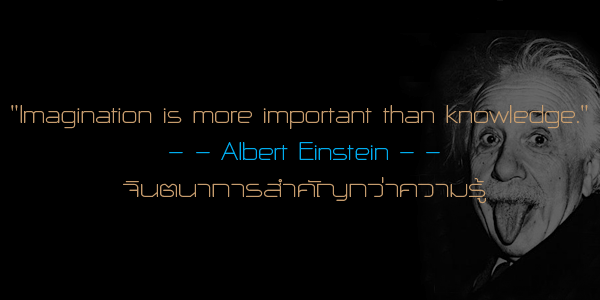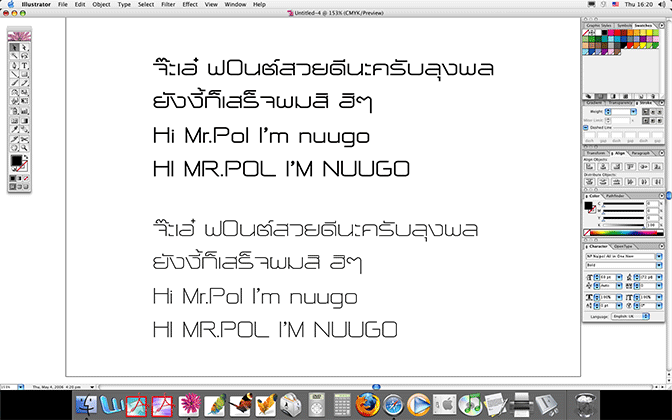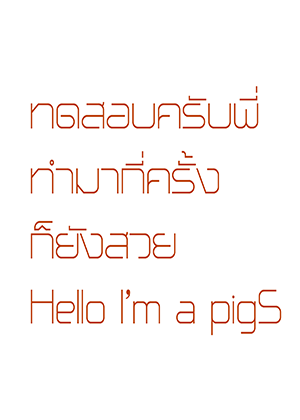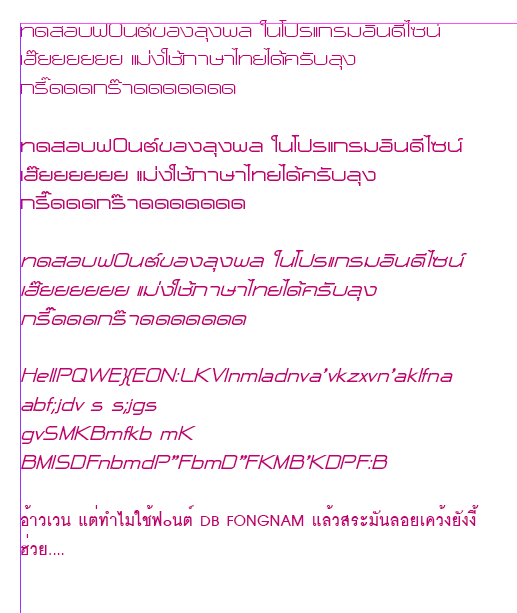
ฟอนท์เก่าเอามาทำใหม่ ช่วยวิจารณ์+ทดสอบกันหน่อยครับ  กรี๊ดดดดด
มีการปรับเปลี่ยนใหม่ทั้งหมด โดยเฉพาะพวก จ ฉ น ม ท พวกนี้ครับตัวเดิมมันหยักน้อยเวลาใช้ตัวเล็กมันไม่แจ่ม
ตัวหนา ตัวเอน ทำใหม่หมด
จัด kerning เพิ่มเติม
ทำเป็นฟอนท์ .otf ซึ่งเป็นแพลตฟอร์มใหม่ล่าสุดของฟอนท์ จึงอยากให้เอาไปลองกันหน่อยครับ เพราะเข้าใจว่าในอนาคตอาจจะมีการทำฟอนท์ .otf กันเป็นส่วนใหญ่ รวมทั้งผมต้องการทดสอบตัวเทมเพลตด้วยครับ เท่าที่เจอตัวเทมเพลตถ้าทำเป็น .otf จะมีปัญหาบางตัวกับ Photoshop CS ซึ่งต้องเปลี่ยนชื่อบาง Glyph เพราะฉะนั้นใครอย่าเพิ่งเอาไปทำเป็นฟอนท์ .otf นะครับ รอเวอร์ชันต่อไป โดยเฉพาะใครใช้แมครบกวนแจ้งผลด้วยนะครับ
รวมทั้งช่วยวิจารณ์หน้าตาฟอนท์ได้เต็มที่นะครับ เพราะตอนทำ all in one นี่หน้าตาแทบไม่ได้นึกถึงเลย ไม่ได้นึกถึงรายละเอียดอะไรมาก ตอนนั้นทำเพื่อทดสอบว่าฟอนท์เดียวมันจะใช้ได้ทุกโปรแกรมหรือเปล่า เพราะก่อนนั้นฟอนท์ส่วนใหญ่จะใช้กับโปรแกรมออฟฟิศอย่าง กับพวกโปรแกรมกราฟิคอีกอย่าง เป็นที่มาของชื่อ all in one
illus cs1
Photoshop cs1
ฟ๐นต์สวย  กรี๊ดดดดด
ใน Indesign CS Version 3.0 ครับ
ถามคุณ nuugo อีกทีครับ
mac os x ใช่มั้ยครับ
คือฝรั่งเขาบอกว่าฟอนท์ .otf นี่มันจะใช้กับแมคที่ต่ำกว่า mac os x ได้ด้วย แต่ต้องใช้ atm ด้วยมั้ง เห็นเขาบอกว่าใช้ได้เพียง 256 glyphs แรก เดี๋ยวนี้ไม่รู้่ว่าคนใช้แมคเขาใช้แมคต่ำกว่า mac os x กันอยู่หรือเปล่า อยากทราบผลเหมือนกันว่ามันจะใช้ไทยได้หรือเปล่า ...
ยังกล้าๆกลัวๆครับ ที่จะเอา .otf ไปใช้จริงๆ
เดี๋ยวคนโหลดไปก็งงๆอีก ว่ามันใช่ฟอนต์รึเปล่า
เพราะเราคุ้นเคยกับ .ttf มานมนาน (มากๆ)  ง่ะ
สงครามฟอนท์น่าจะจบที่ opentype ท้ายสุดน่าจะเป็น .otf ครับ
ตอนนี้อยู่ในช่วงระยะของการเปลี่ยนแปลง (โม้ตามบักสีดา  แป่ว)
ดูเหมือนลุงโก้กำลังดีใจแทบคลั่งที่นาน ๆ ทีจะมีฟอนต์ที่ใช้กับ Mc ได้ ฮิ้ววว